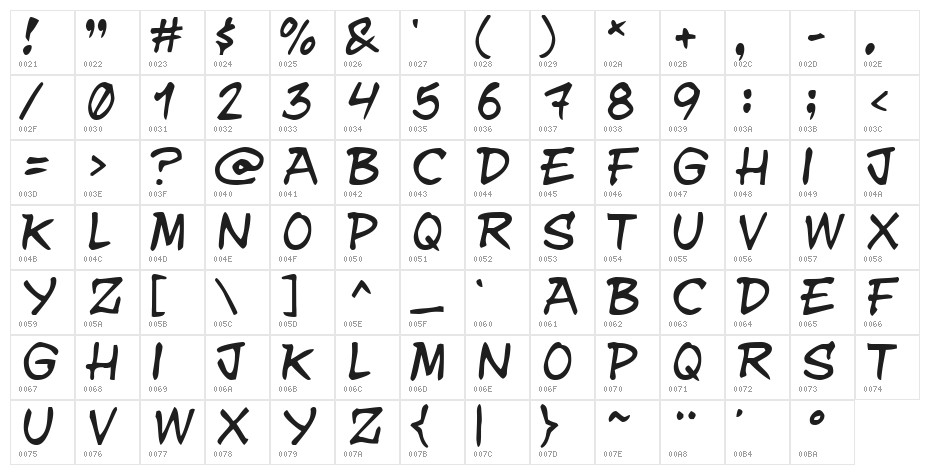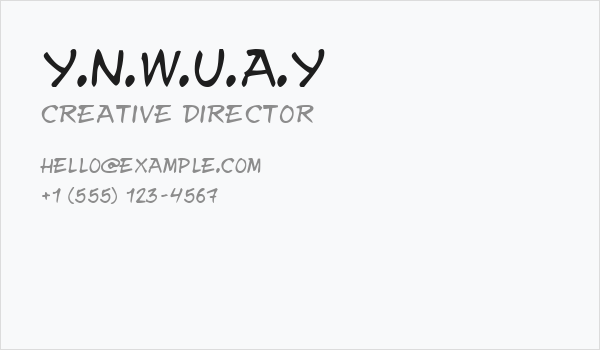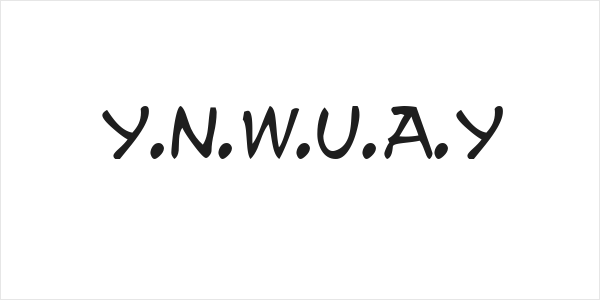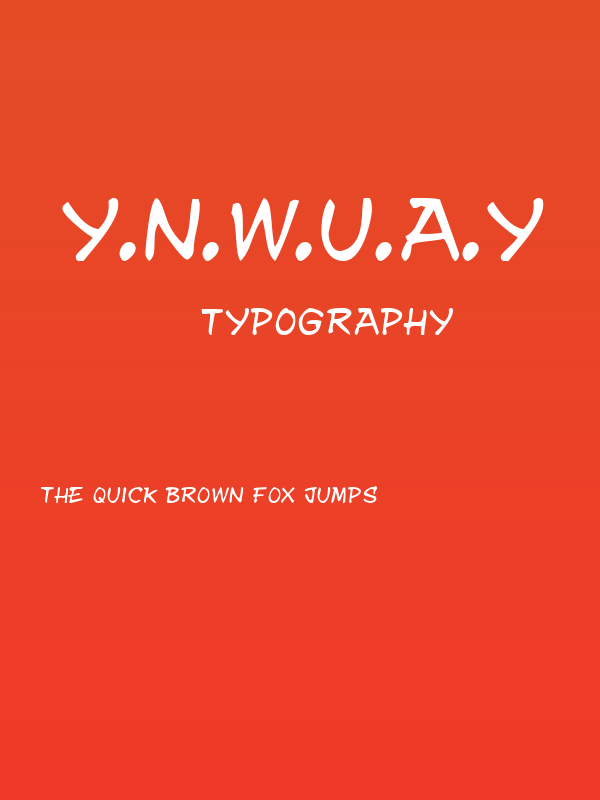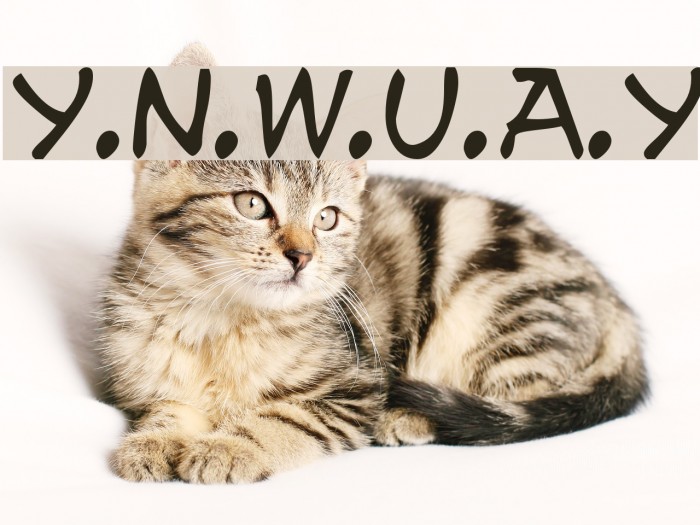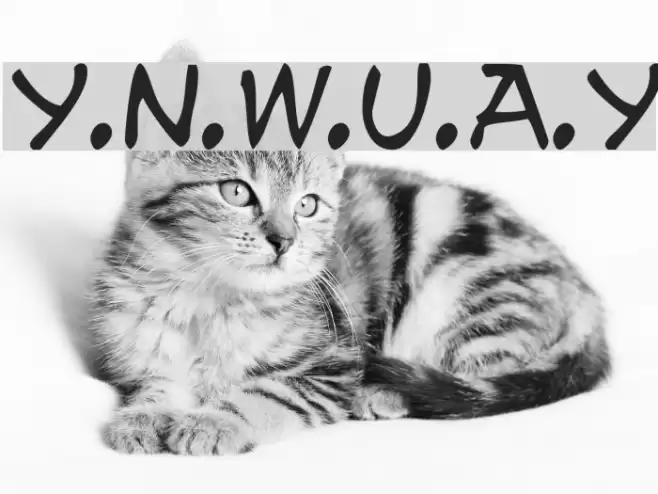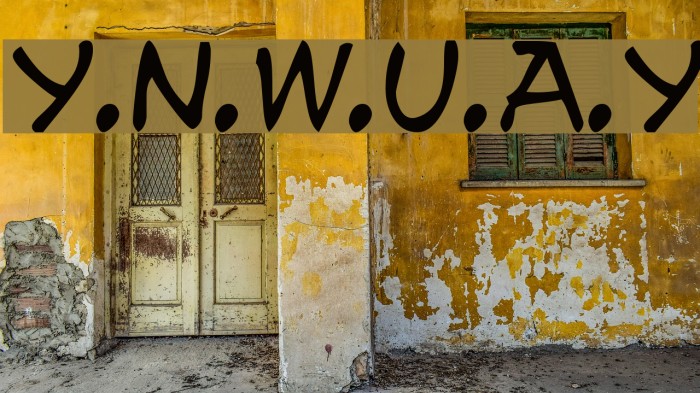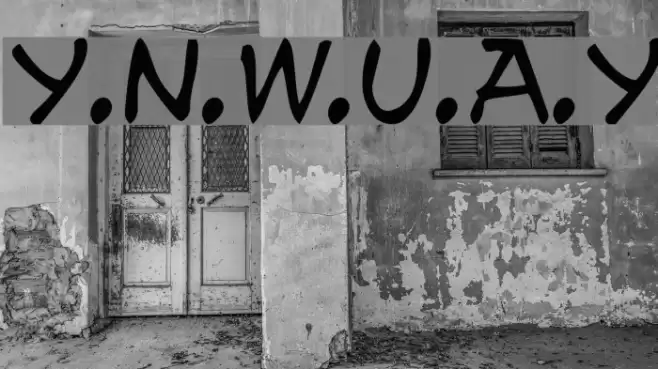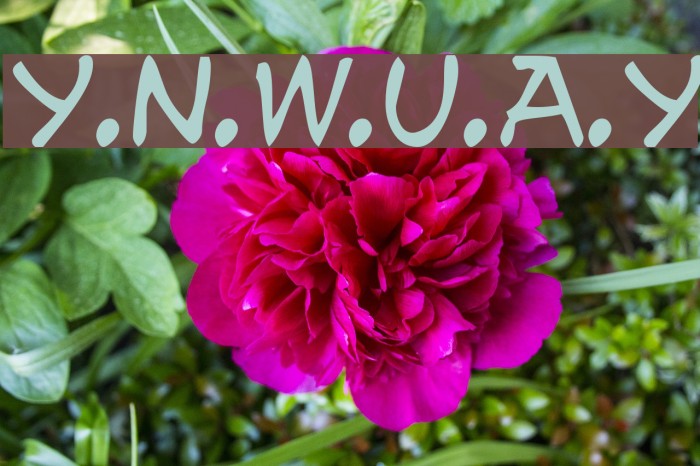
y.n.w.u.a.y Font
| Рекомендуемые проекты | Ideal for greeting cards, invitations, posters, and branding projects that require a personal and informal touch. |